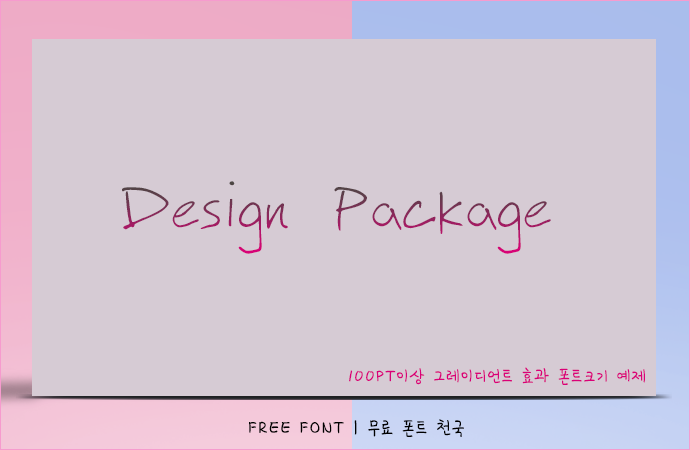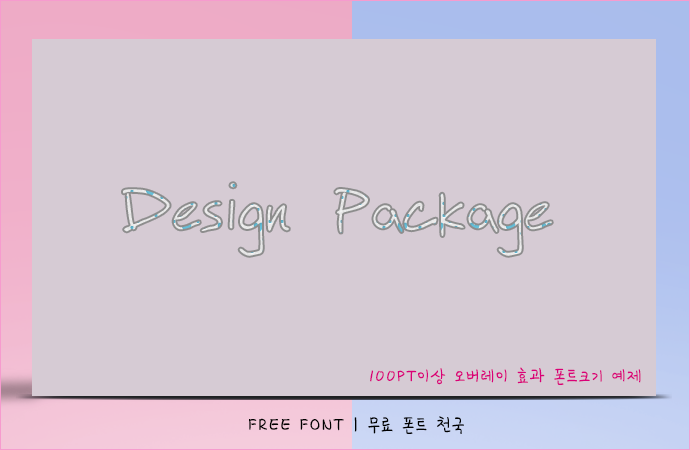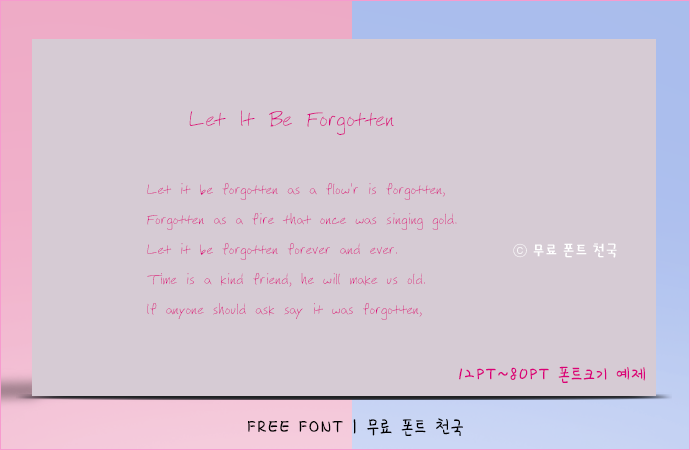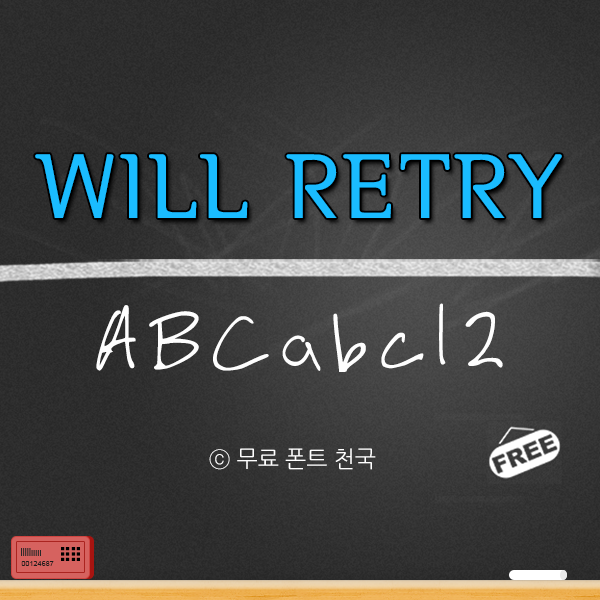
필기체 스타일의 Will Retry 영문폰트
Will Retry 폰트 정보
필기체 스타일로 제작된 Will Retry 영문 폰트입니다. 글자 간격과 문장과 문장 간격이 조금 넓어 얇은 스타일의 폰트임에도 불구하고 가독성이 매우 좋은 서체입니다. 20pt 이하의 작은 서체에서도 사람이 쓴 듯한 느낌을 느길 수 있습니다. Will Retry 서체는 누구나 무료로 사용 가능한 프리 폰트입니다.
Will Retry 폰트 # 미리보기
Will Retry 폰트, 12~80PT 크기로 적용한 효과
Will Retry 폰트, 100PT 크기 이상으로 작업한 오버레이 효과
Will Retry 폰트, 100PT 크기 이상으로 작업한 그레이언트 효과